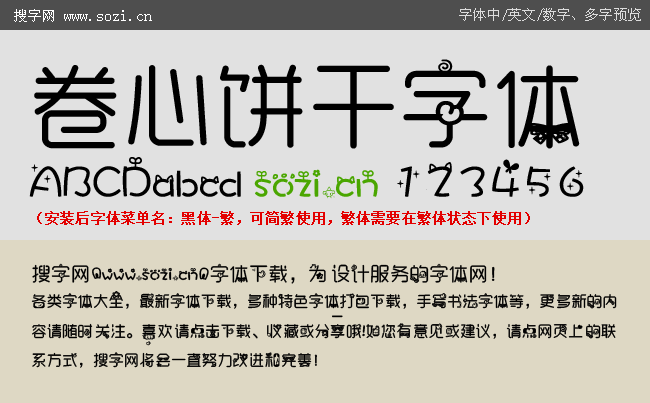
卷心餅干字體
搜字網(wǎng)給大家提供一款卷心餅干字體手機中文字體下載。這款手機字體是將悅圓體字體為原形,字體間嵌入可愛的卡通圖案。造字工房悅圓常規(guī)字體為圓體字形,結構秉承悅黑系列,筆畫風格簡潔,柔美優(yōu)雅。加入卡通圖案后趣味性實足,又保持了文字的識別度,特別適合喜歡手機字體個性一些的朋友在手機上安裝使用。